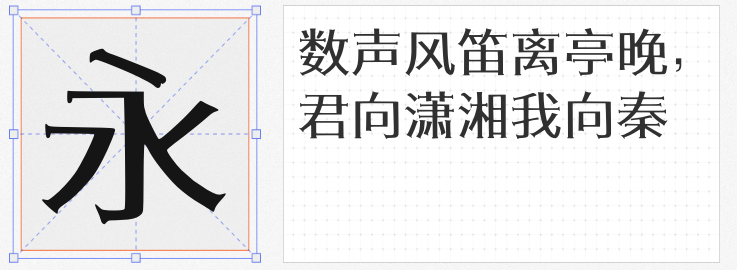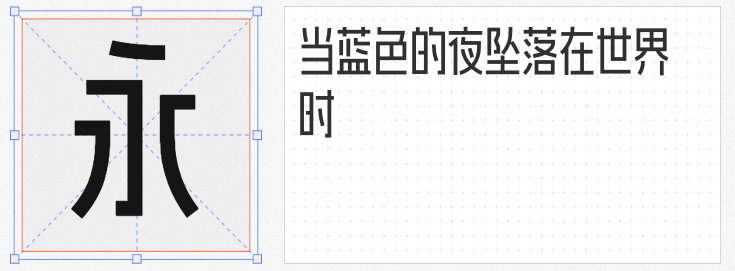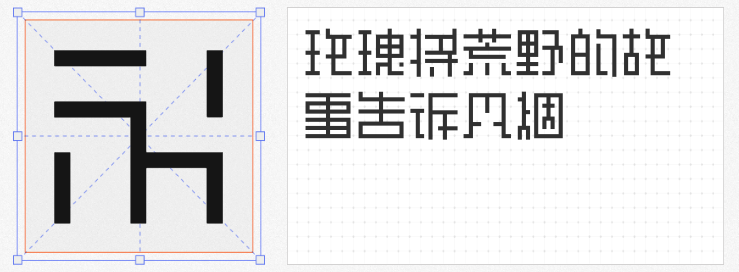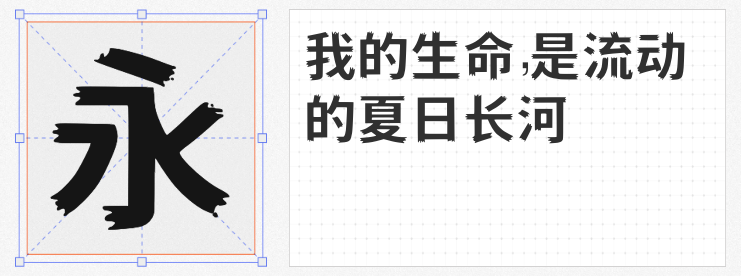
在商业设计同质化严重的今天,一款独特的字体往往能成为视觉表达的点睛之笔。本文精选四款兼具艺术性与实用性的免费商用字体,涵盖像素重构、人文长体、宋体新解与黑体解构四大创意方向,助力设计师突破创作边界。
1. 余繁离形体
这款类像素体以11×11的网格为画布,通过“部件优先简化”策略重构汉字形态。设计师巧妙运用点阵与横竖线的排列组合,将复杂结构转化为几何韵律——如“目”字经三级简化最终呈现为“口”的极简形态。这种数字时代的文字解构,既保留了像素艺术的复古未来感,又通过理性取舍创造出独特的视觉张力,尤其适合科技主题海报、游戏界面等需要工业质感的设计场景。
2. 爱点风雅黑长体
基于经典黑体改良的这款长体字,以1.5:1的独特长宽比重塑汉字形态。纤细的中宫与舒展的笔画形成优雅的视觉韵律,既保留了黑体的现代感,又融入了书法美学的飘逸气质。其免费商用政策覆盖个人到企业全场景,从品牌VI到视频字幕,都能以东方雅韵传递时尚态度。
以宋体为基因的创意变体,通过棱角分明的笔画与内收的弧度形成视觉张力。这种“外刚内柔”的设计语言,完美诠释了“一诺千金”的品牌承诺,尤其适合餐饮、文创等需要传递信任感的行业。
4. 鼎猎刺猬体
黑体骨架上生长出锯齿状笔锋,如同刺猬的尖刺包裹着柔软内核。这种充满叛逆感的字体形态,与《哪吒2》中魔丸哪吒的“锋芒与温情”形成跨次元呼应,为美妆、潮牌等年轻化场景提供极具冲击力的视觉表达。